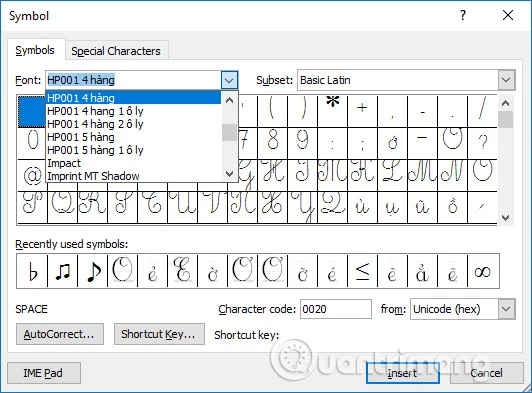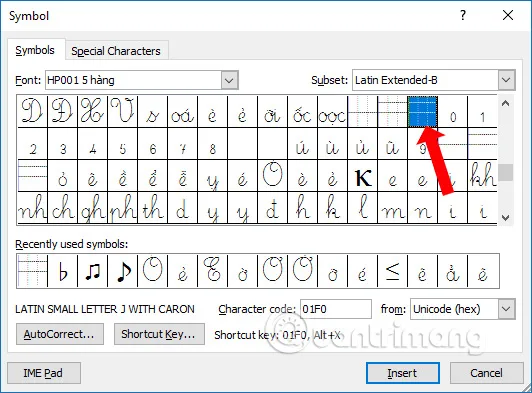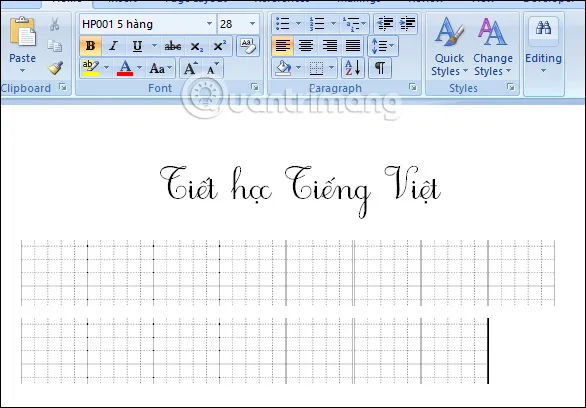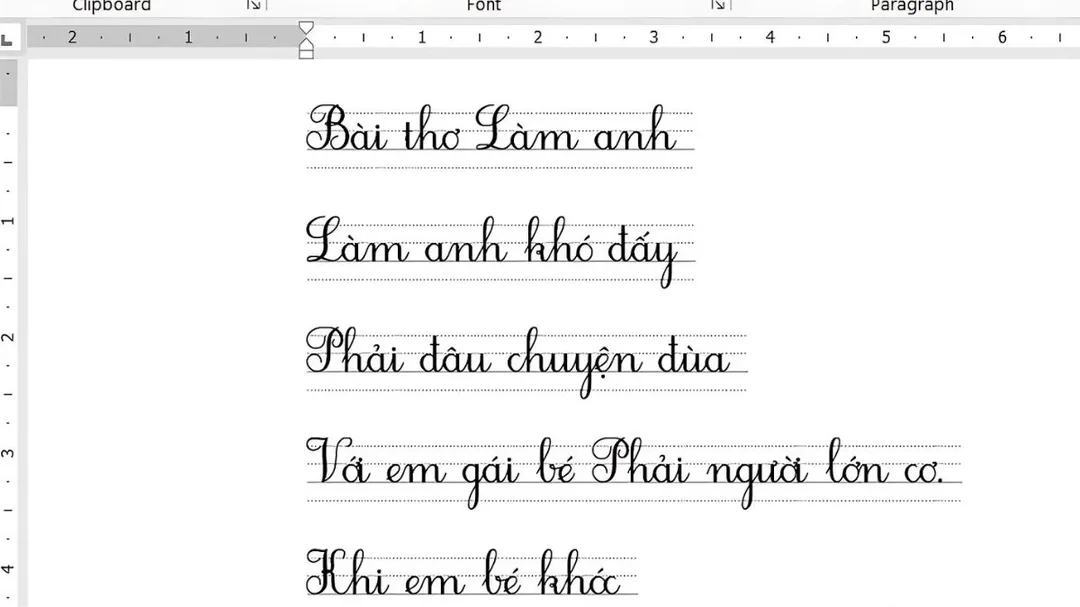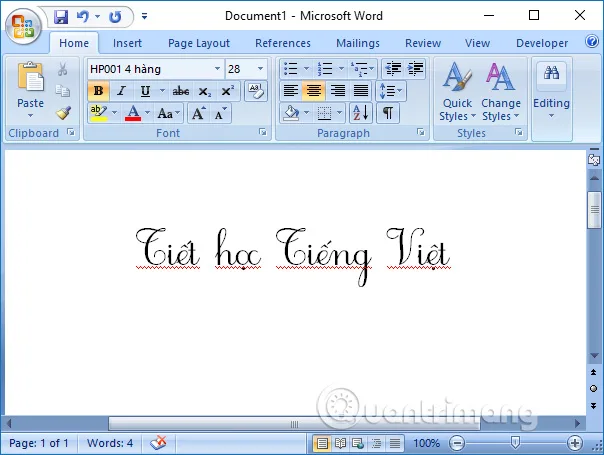
Cách cài font chữ tiểu học vào máy tính giúp giáo viên, phụ huynh và học sinh dễ dàng soạn bài tập viết chữ theo chuẩn Bộ Giáo dục. Bộ font bao gồm các kiểu chữ có kẻ ô ly, 4 hàng, 5 hàng — phù hợp để in bài luyện viết tại nhà hoặc soạn giáo án điện tử. Hướng dẫn dưới đây áp dụng cho cả Windows 10 lẫn Windows 11, kèm cách sử dụng font trong Microsoft Word.
Font chữ tiểu học là gì và dùng để làm gì
Font chữ tiểu học là bộ phông chữ được thiết kế theo đúng mẫu chữ viết tay chuẩn của chương trình giáo dục Tiểu học Việt Nam. Các font này mô phỏng nét chữ viết tay trên vở ô ly, giúp học sinh nhận diện đúng hình dáng, kích thước và tỷ lệ nét chữ.
Bộ font phổ biến nhất gồm: HL Hoctro, HP001 4 hàng, HP001 4 hàng 1 ô ly, HP001 4 hàng 2 ô ly, HP001 5 hàng, HP001 5 hàng 1 ô ly. Mỗi font có ký tự kẻ dòng riêng, cho phép tạo vở ô ly ngay trong Word.
Font chữ tiểu học giúp rèn luyện chữ viết
Font chữ tiểu học thiết kế theo chuẩn Bộ Giáo dục
Ưu điểm khi sử dụng font chữ tiểu học
Cấu trúc chuẩn theo quy định: Font đảm bảo độ cân đối giữa các nét theo tỷ lệ chuẩn, giúp trẻ hình thành thói quen viết đúng ngay từ đầu.
Tương thích với vở ô ly: Font được thiết kế phù hợp kích thước ô ly, giúp trẻ viết đúng dòng kẻ, giữ chữ ngay ngắn.
Hỗ trợ luyện viết hiệu quả: Các nét chữ có điểm bắt đầu và kết thúc rõ ràng, giúp trẻ rèn viết liền mạch, đúng nét.
Hình dáng thân thiện: Nét chữ mềm mại, bo tròn, đơn giản hóa giúp học sinh dễ phân biệt và ghi nhớ mặt chữ.
Hướng dẫn trực quan cài font chữ tiểu học và tạo vở ô ly
Cách sử dụng font chữ tiểu học trong Word
Sau khi cài đặt thành công, font sẽ xuất hiện trong danh sách font của mọi phần mềm soạn thảo — Word, Google Docs (nếu cài trên máy), PowerPoint.
Chọn font và nhập nội dung
Mở Microsoft Word, nhấn vào ô font trên thanh toolbar, gõ tên font — ví dụ “HP001 4 hàng” — và chọn từ danh sách xổ xuống.
Tìm font chữ tiểu học trong Word
Gõ tên font tiểu học tìm nhanh
Nhập nội dung và font sẽ hiển thị đúng kiểu chữ viết tay tiểu học, bao gồm cả dấu thanh tiếng Việt.
Nhập nội dung với font tiểu học
Nội dung hiển thị đúng phong cách chữ viết tay tiểu học
Tạo kẻ ô ly trong Word
Font chữ tiểu học đi kèm ký tự kẻ ô ly đặc biệt. Để chèn ô ly, vào Insert → Symbol → More Symbols, chọn font HP001, tìm ký tự kẻ ô ly trong bảng ký tự.
Chèn ký tự ô ly
Chọn More Symbols để tìm ký tự kẻ ô ly
Chọn kẻ ô ly
Chọn ký tự kẻ ô ly phù hợp
Nhấn Insert nhiều lần để tạo dãy kẻ ô ly dài theo hàng.
Dòng kẻ ô ly trên Word
Kết quả dãy kẻ ô ly trong Word
Chỉnh dòng kẻ ô ly bị tách rời
Nếu các dòng kẻ ô ly bị tách rời (có khoảng trống giữa các dòng), cần điều chỉnh Line Spacing.
Vào Home → Line Spacing → Line Spacing Options. Đặt Line spacing thành Exactly với giá trị phù hợp (thường 30–36 pt tùy font).
Chỉnh Line Spacing
Mở Line Spacing Options để chỉnh khoảng cách dòng
Điều chỉnh thông số khoảng cách
Đặt Line spacing thành Exactly để dòng kẻ liền mạch
Font HL Hoctro phù hợp nhất cho soạn bài giảng điện tử vì không có dòng kẻ, trình chiếu trên projector dễ đọc. Các font HP001 phù hợp in bài tập trên giấy vì có kẻ ô ly tích hợp sẵn.
Nắm vững cách cài font chữ tiểu học vào máy tính giúp giáo viên nhanh chóng soạn bài tập luyện viết, phụ huynh in bài tập cho con tại nhà, và học sinh làm quen với mẫu chữ chuẩn ngay trên màn hình máy tính.